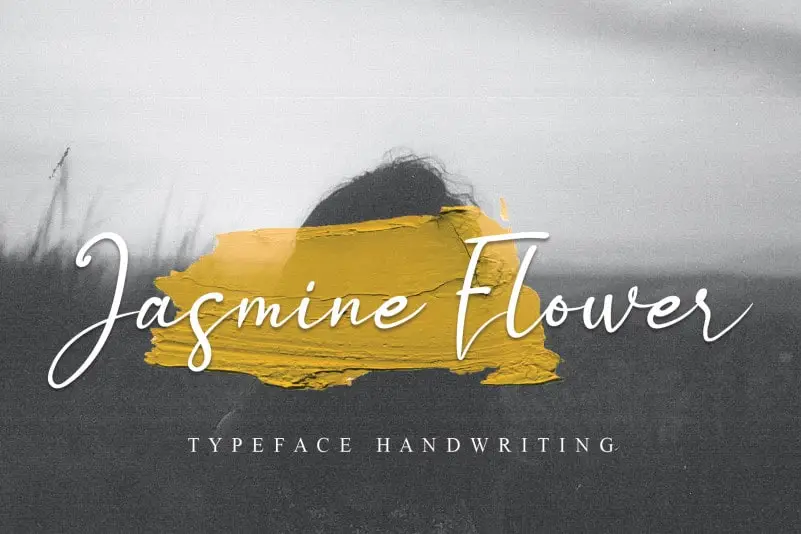
Jasmine Flower Handwritten Font – Fonte Grátis
Jasmine Flower Handwritten Font
Jasmine Flower Handwritten Font é uma elegante e suave fonte feita à mão. Ela possui traços fluidos e atual, perfeita para qualquer tema ou projeto. Esta font se destaca não apenas pela sua aparência sedosa e delicada, mas também pelo seu charme cíntico que traz um toque de sofisticação e elegância. Seja para o design de logotipos, criações gráficas, mensagens pessoais ou até mesmo para personalizar cartões de aniversário, essa fonte vai ser sua escolha predileta. Com a Jasmine Flower Handwritten Font, você encontra uma fonte única e sofisticada que se adapta perfeitamente às necessidades de qualquer projeto visual.